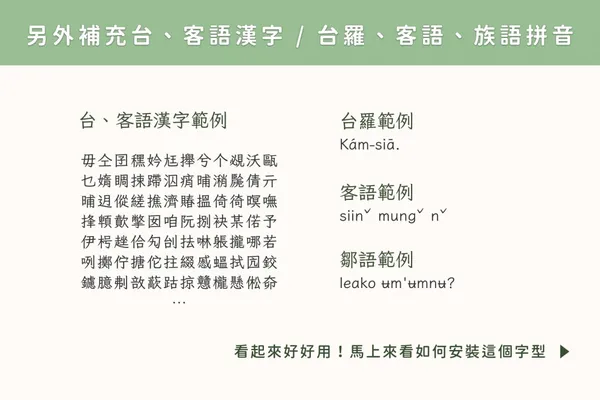
「芫荽」字型加入LINE,可以優化用戶在LINE輸入繁體中文時的使用體驗,此款字型補充了台灣本土語言用字(如客語漢字、台語漢字、原住民族語羅馬字等),能讓言詞的使用更到位。
「芫荽」字型是在2022年時,由字嗨發起人But Ko基於Fontworks Klee One改作,也是台灣第一套開源的硬筆楷書字型。
傳統的Klee(クレー)字型因兼具楷體與仿宋的筆調及其高易讀性,受許多中文使用者的喜愛。然而畢竟是日文字型,雖然字數不少,但在使用上仍有一定程度的缺字。「芫荽」便由此而生,在保有傳統楷體和仿宋風格上改善了缺字的狀況,減少排版上的不便。
「芫荽」字型在保有傳統楷體和仿宋風格上,改善了缺字的狀況,減少人員排版上的不便。
「芫荽」補充了台灣本土語言用字(如客語漢字、台語漢字、原住民族語羅馬字等)。
「芫荽」字型外型溫潤,線條易讀,且調整過字形,使其更貼近教育部標準字體,加上補充台客語用字,因此更貼近台灣需求,是一款適合學齡教育使用的字體。
「芫荽」字型做過調整,使其更貼近教育部標準字體。